中英文字体搭配技巧。解锁你不知道的细节
在设计banner或海报时,
中英文搭配应该算是一门基本功了,
当然了,完成任务容易,想达到一定高度就难了
无论字体气质的选择,还是排版组合的功底,都不是简简单单就能搞定的
普通的中英文搭配大概是这样
大师级是这样
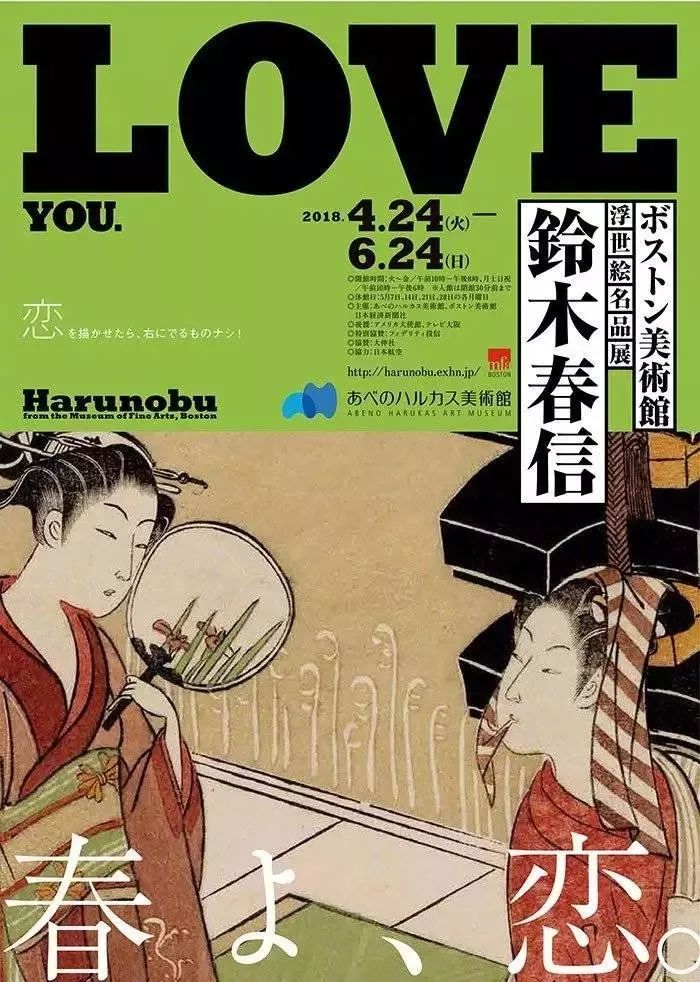
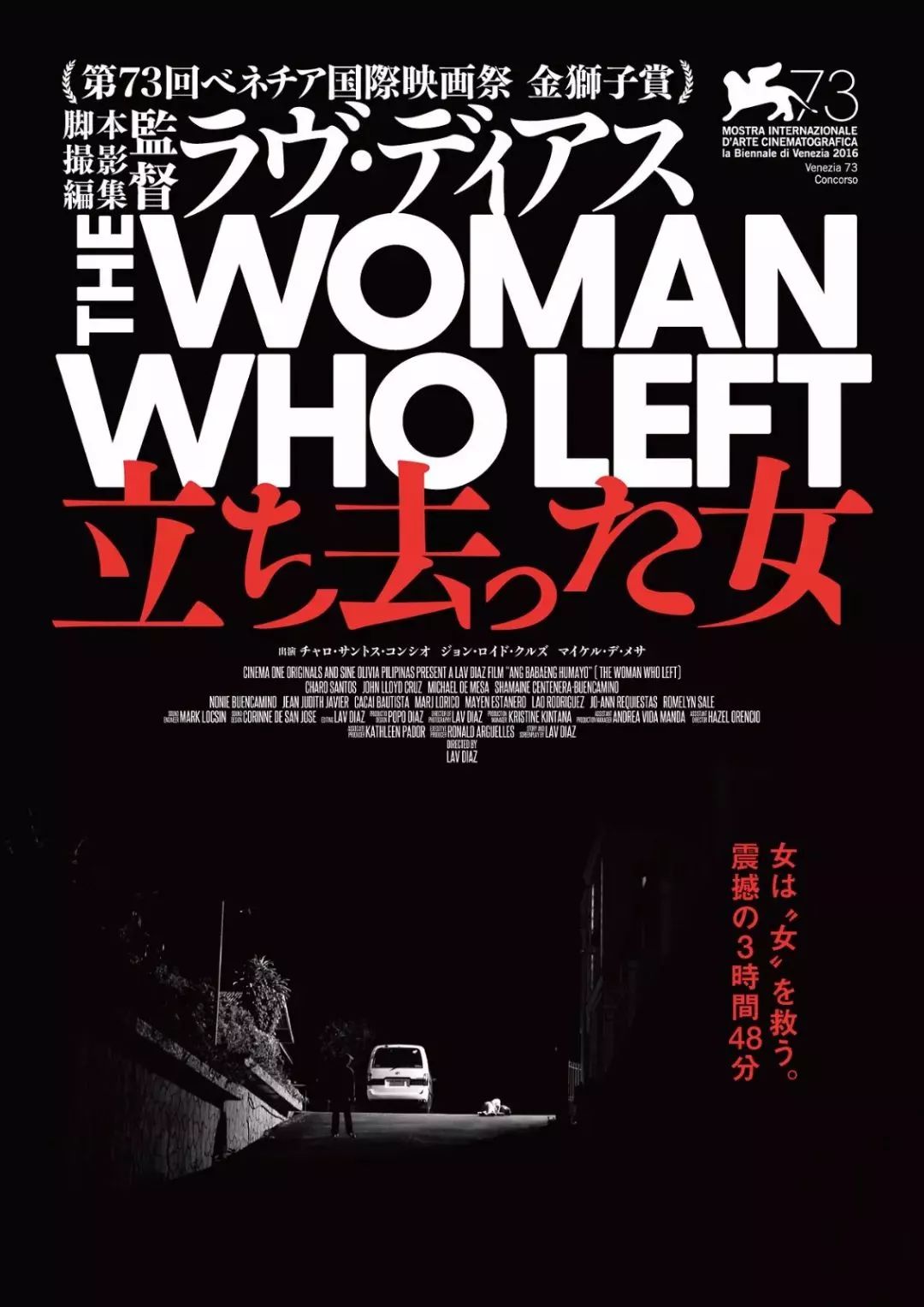
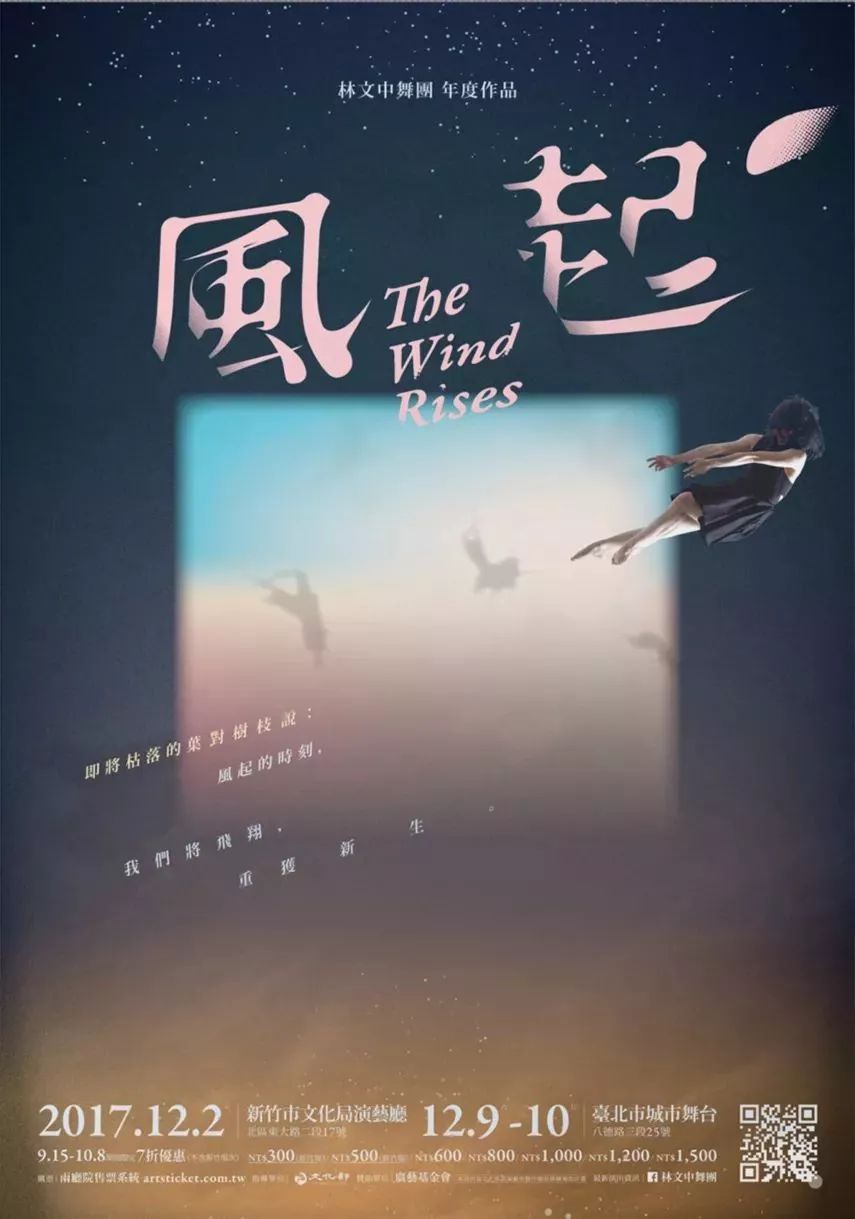
普通和大师级的差距你一眼就能看明白,
如果你觉得自己这方面还有欠缺,